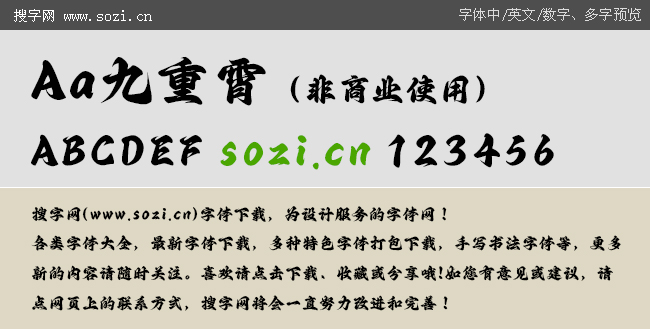
Aa九重霄
搜字網(wǎng)給大家提供一款A(yù)a九重霄(非商業(yè)使用)中文字體下載,Aa九重霄是一款手寫風(fēng)格的書法字體,該字體筆觸適中,筆畫隨性,書寫大氣,結(jié)構(gòu)肆意灑脫,視覺效果非常棒。適合應(yīng)用于海報設(shè)計、包裝設(shè)計、網(wǎng)頁設(shè)計等應(yīng)用(此字體為個人非商用版,商用可以聯(lián)系QQ:1006760504)。